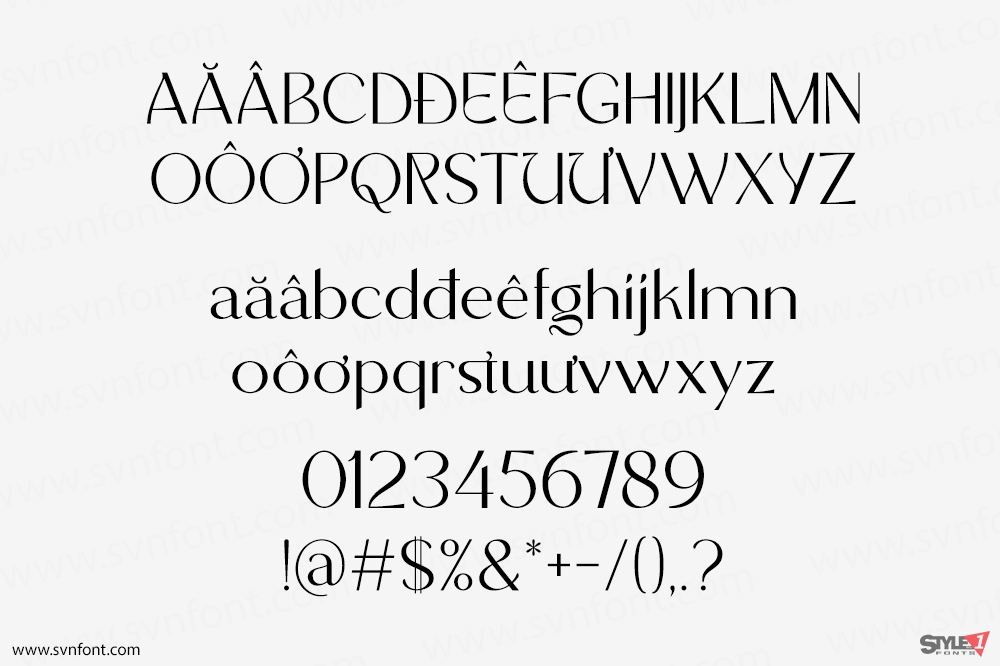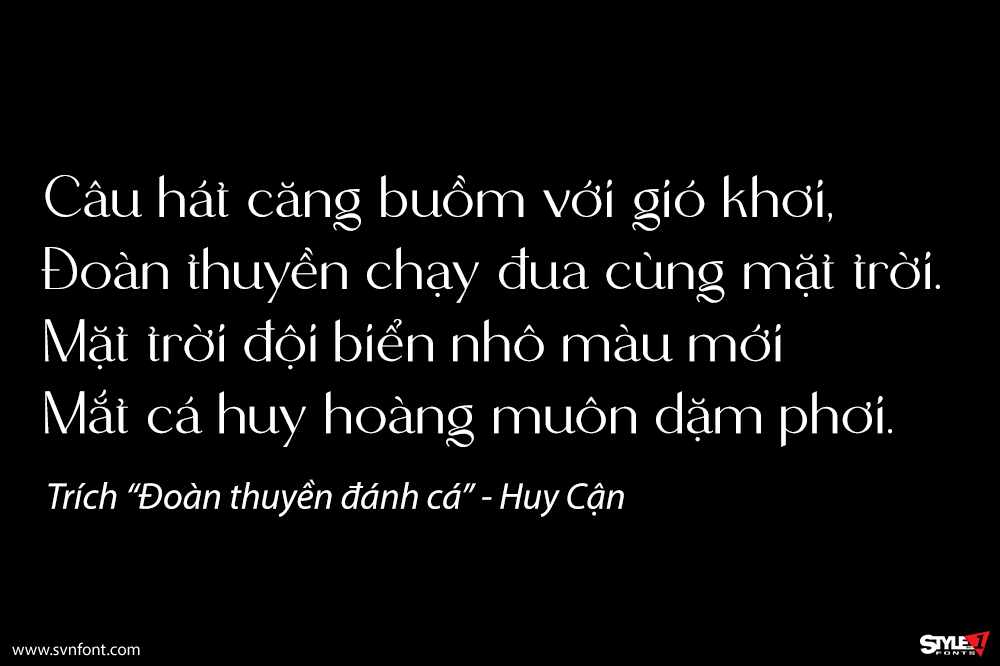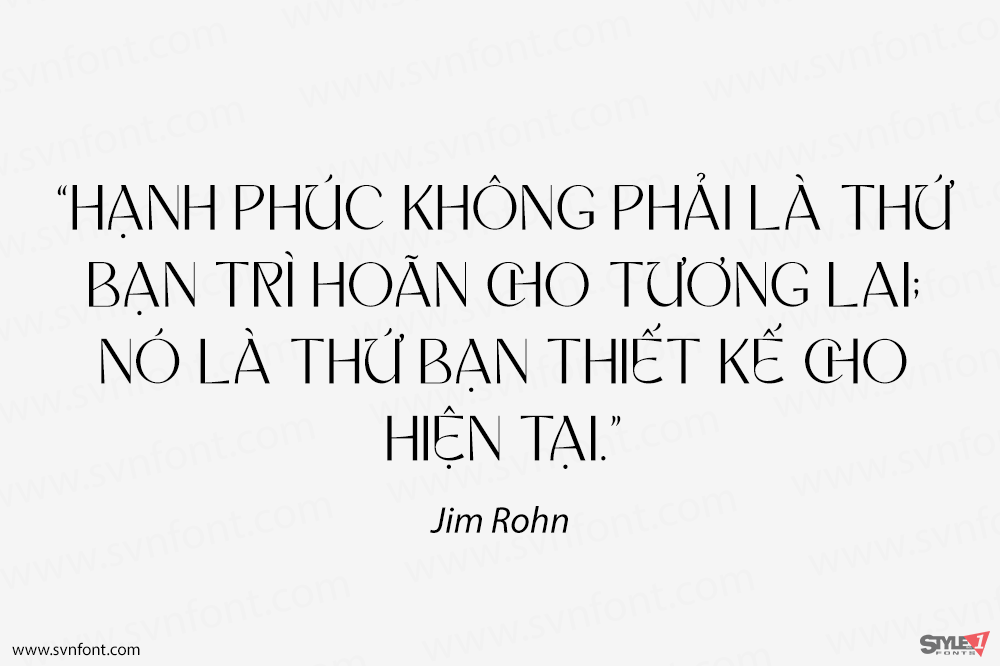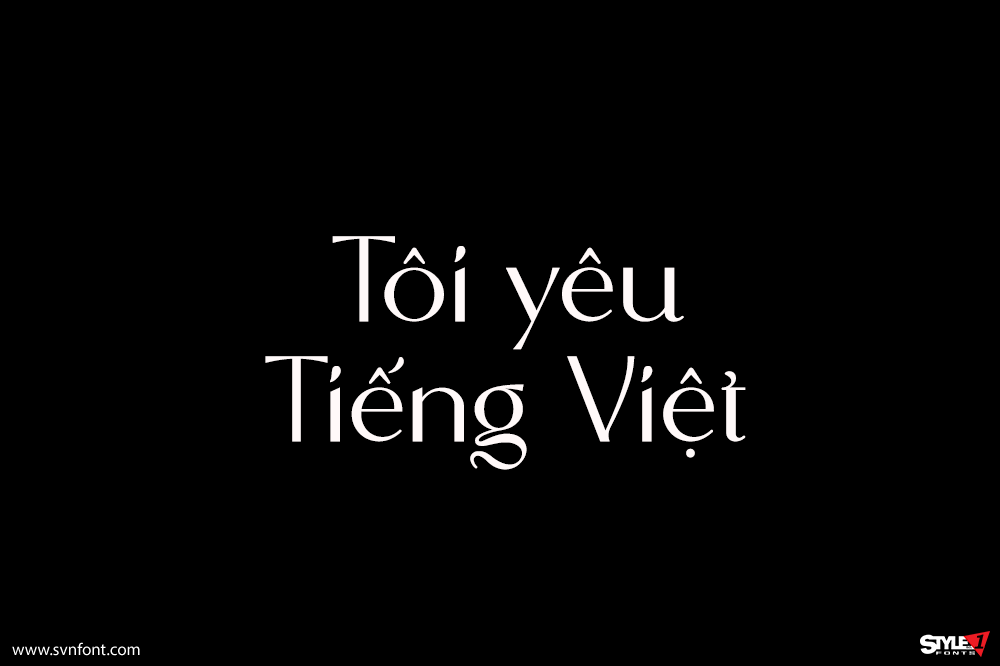
Archattes là một font sans serif thanh lịch và đẹp mắt. Font giúp nâng tầm nhiều ý tưởng sáng tạo, từ thiệp, branding, nhãn mác cho đến nhiều ứng dụng khác. Hãy thêm Archattes vào các dự án thiết kế của bạn để tạo nên những sản phẩm nổi bật và khác biệt.
Nhà thiết kế: Hayinah
Nhà phát hành: Hayinah